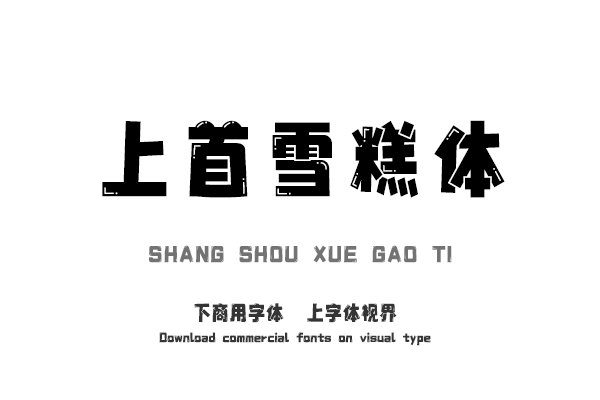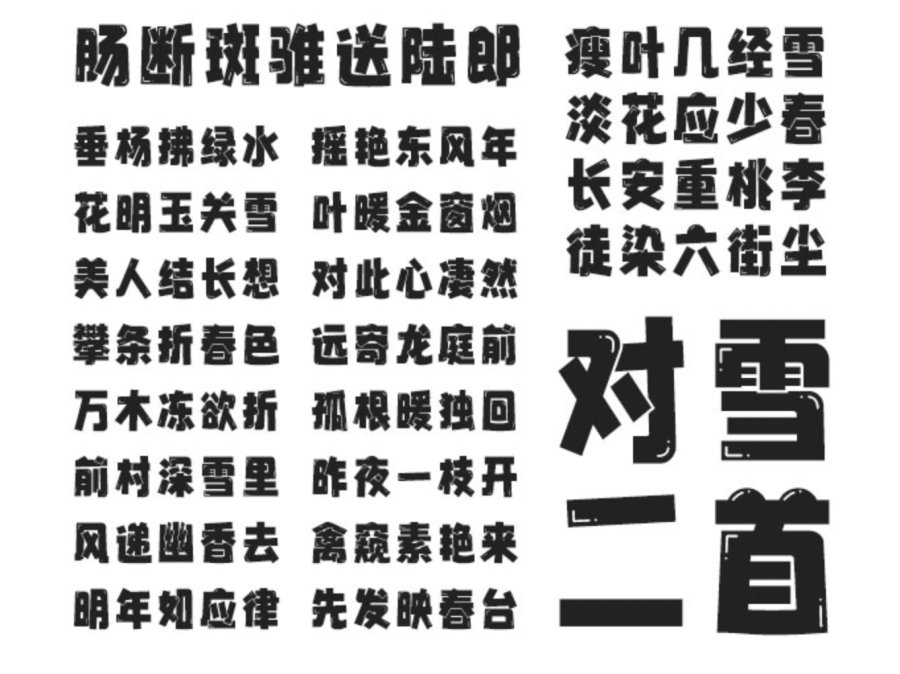
消暑特效字体-上首雪糕体上线
这个夏天全国大部分地区都被高温折磨,炎热的天气还没有减退的意愿,今天我们送上这款消暑特效字体-上首雪糕体,希望酷暑早点过去,凉爽的天气早点到来。
上首雪糕体
上首雪糕体字体萌动可爱,富有灵性,特点突出,别具一格,这不禁联想到炎炎夏日中圆滚滚亮晶晶的冰块,凉爽而解渴的雪糕,让人心情舒畅,清凉一夏。
上首雪糕体
该字体适用于搭配标志、广告标语、商业广告等高端属性。字体视界平台已取得「上首雪糕体」字体的官方代理授权,并有权为您提供字体授权服务。
上首雪糕体
字库品牌: 上首造字